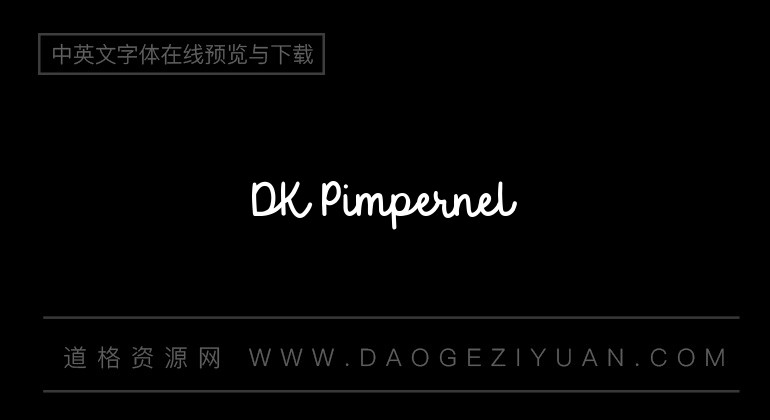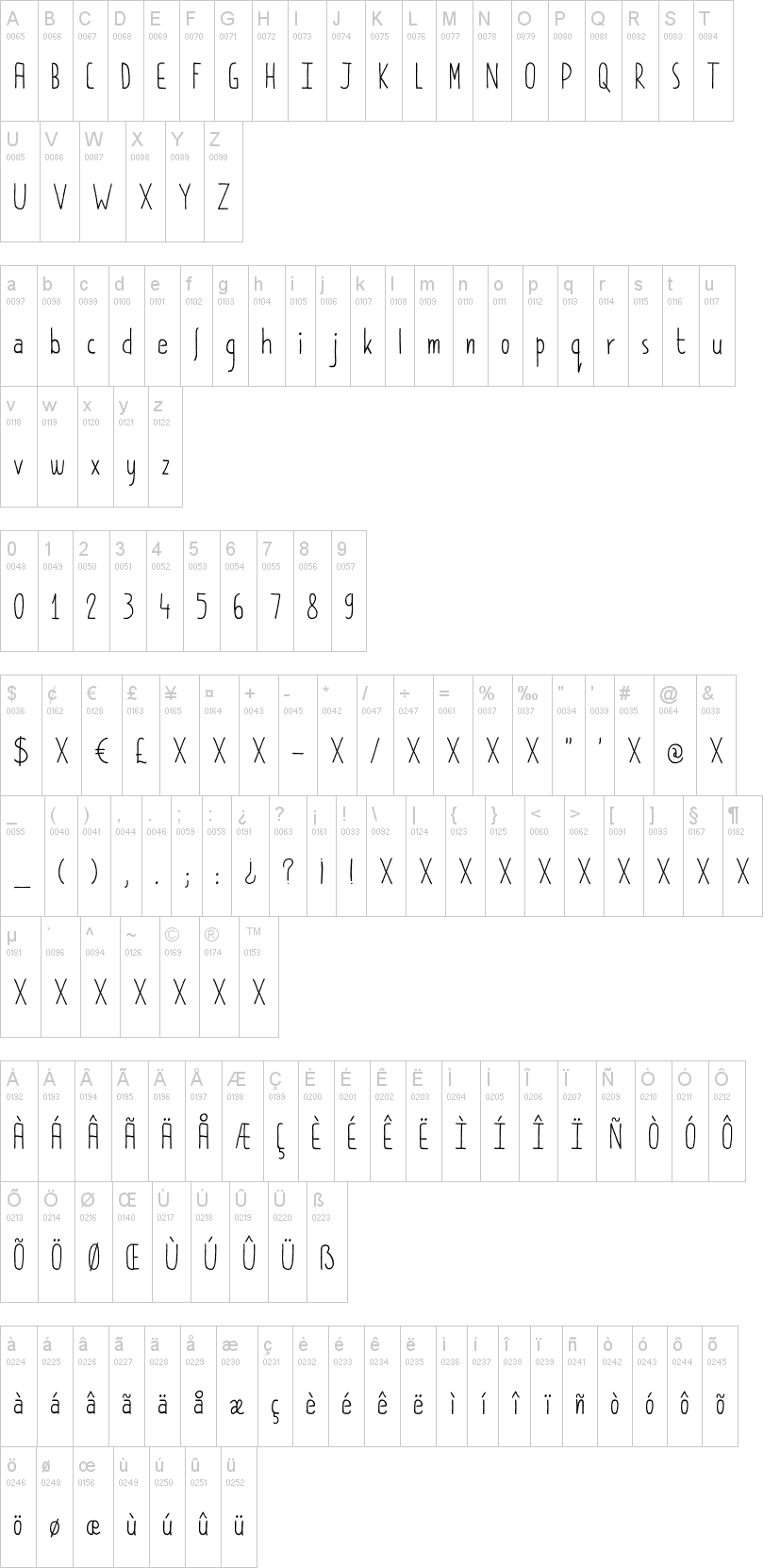
DK Pimpernel 是一种手写风格的字体,它由字体设计师 Hanoded 设计。这种字体具有非常独特的外观,其特点是字母形状不规则、线条曲折,仿佛是手写的效果。 DK Pimpernel 字体非常适合用于设计海报、传单、广告等宣传材料中,因为它的字母形状非常独特,能够很好地吸引人们的眼球。此外,它还适合用于设计一些艺术品、手工制品等产品的标签或包装上,给人一种手工制作的感觉。 该字体包含了常见的英文字母大小写、数字和标点符号,以及一些特殊的字符和装饰元素,方便用户进行设计。这个字体的授权方式为商业授权,所以需要购买授权后才能在商业项目中使用。内容介绍
DK Pimpernel是一款非常不错的手写艺术字体,具有很好的视觉感,适合于文化类的宣传设计、商业类品牌的广告和产品包装设计以及个性化文字排版等较多场景。